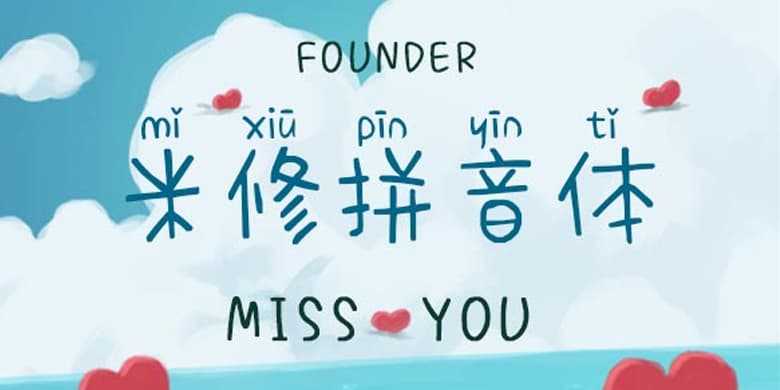
方正手迹-米修拼音体
品牌:方正手迹设计师:刘晔发行时间:2020字库编码:大陆简体(GB2312-80)分类:创意书写字体属性:精品字
这款拼音体笔画简单直接,可爱的口的写法贯穿整个字体,结构灵活多变,显得更加俏皮可爱。再加上添加的拼音,使阅读更加的有趣。适用于少年儿童类的书刊、品牌广告和产品包装设计,以及社交网络的个性化用字。